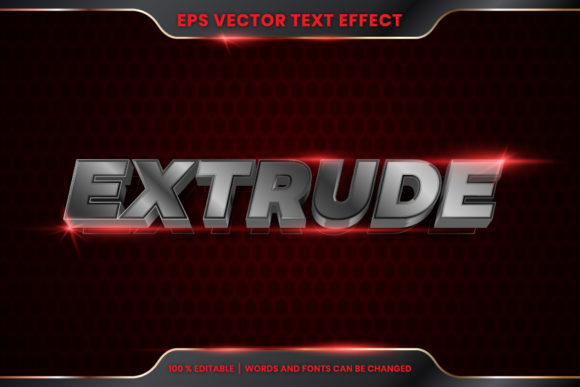
Editable Text Effect - Extrude Text
Jika anda sedang mencari aset berkualiti tinggi seperti Editable Text Effect - Extrude Text, pakej premium ini merupakan pilihan yang hebat untuk projek kreatif anda.
Dicipta dengan ketepatan, Editable Text Effect - Extrude Text menyediakan vektor yang bersih, tipografi yang licin dan lesen komersial untuk ketenangan fikiran.
Sama ada anda mencipta produk POD (Print on Demand), jemputan perkahwinan atau grafik media sosial, Editable Text Effect - Extrude Text amat bersesuaian.